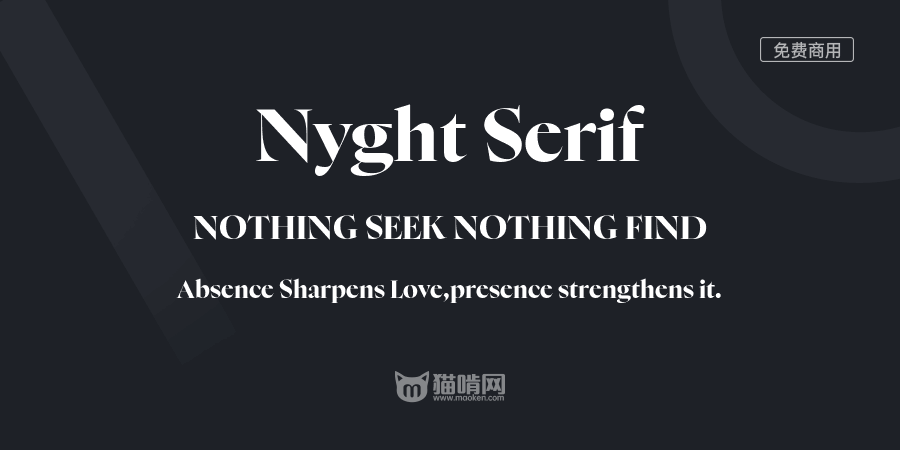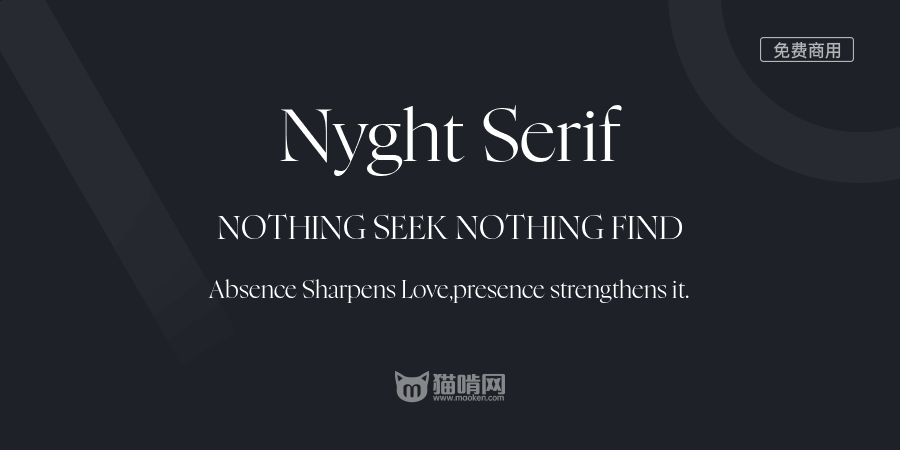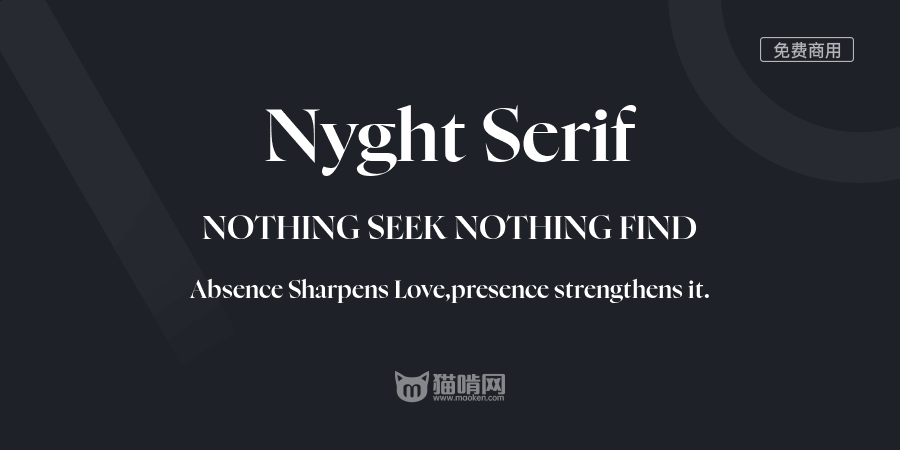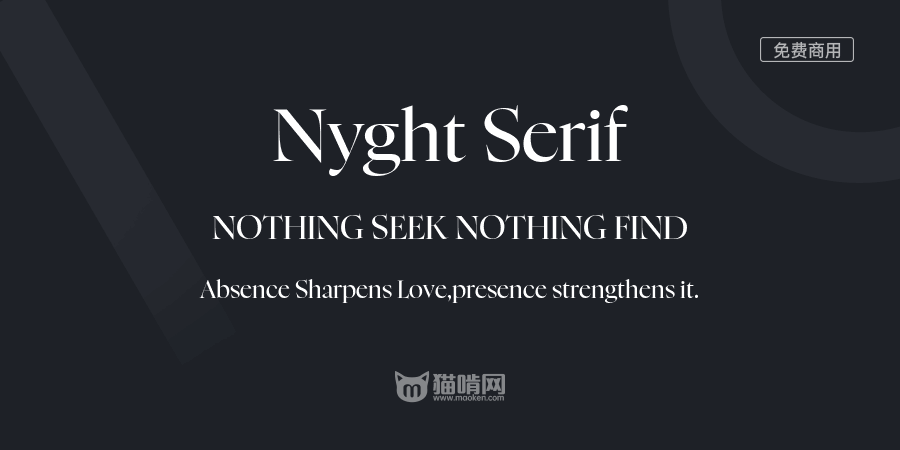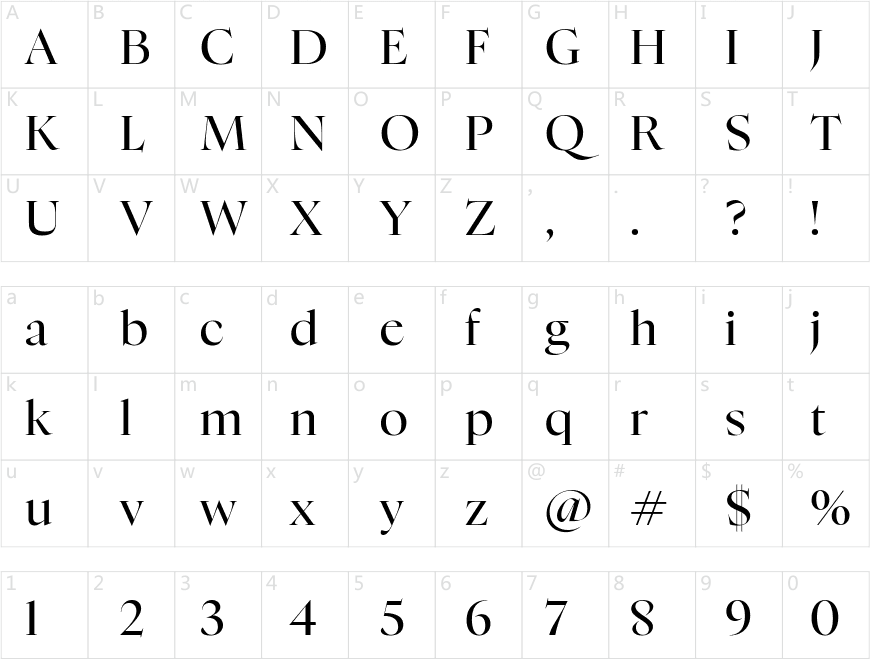
Nyght Serif
Nyght Serif 是一款兼具独特个性的现代衬线字体。其对比鲜明的字形融合了流畅与锐利的曲线,例如刀形衬线与短刺设计。这款字体的创作始于对William Caslon经典字体作品的研究,后在书法艺术与现代衬线字体风格的影响下,设计得以大幅革新。
字体由Maksym Kobuzan设计,支持丰富的拉丁字符集及乌克兰西里尔字母。2023 年,它在第 69 届字体指导俱乐部(TDC)竞赛中荣获 “排版卓越证书奖”。目前 Nyght Serif 已正式发布,但其开发仍在进行中,未来将推出更多更新版本,敬请期待!